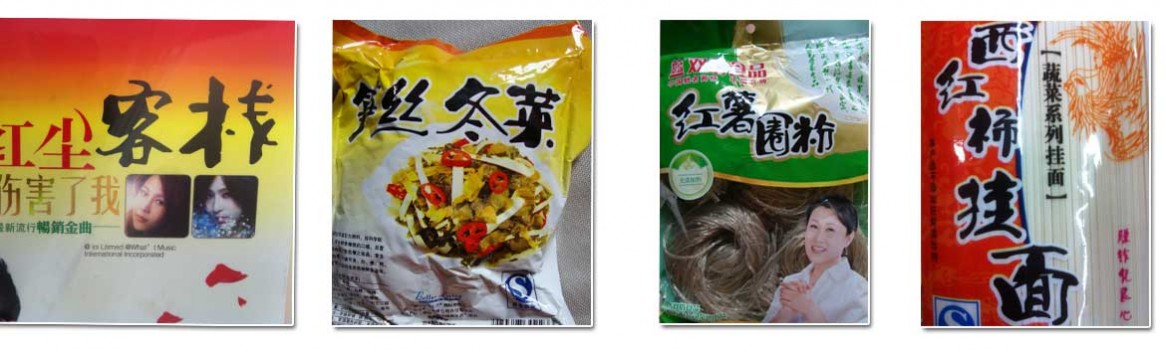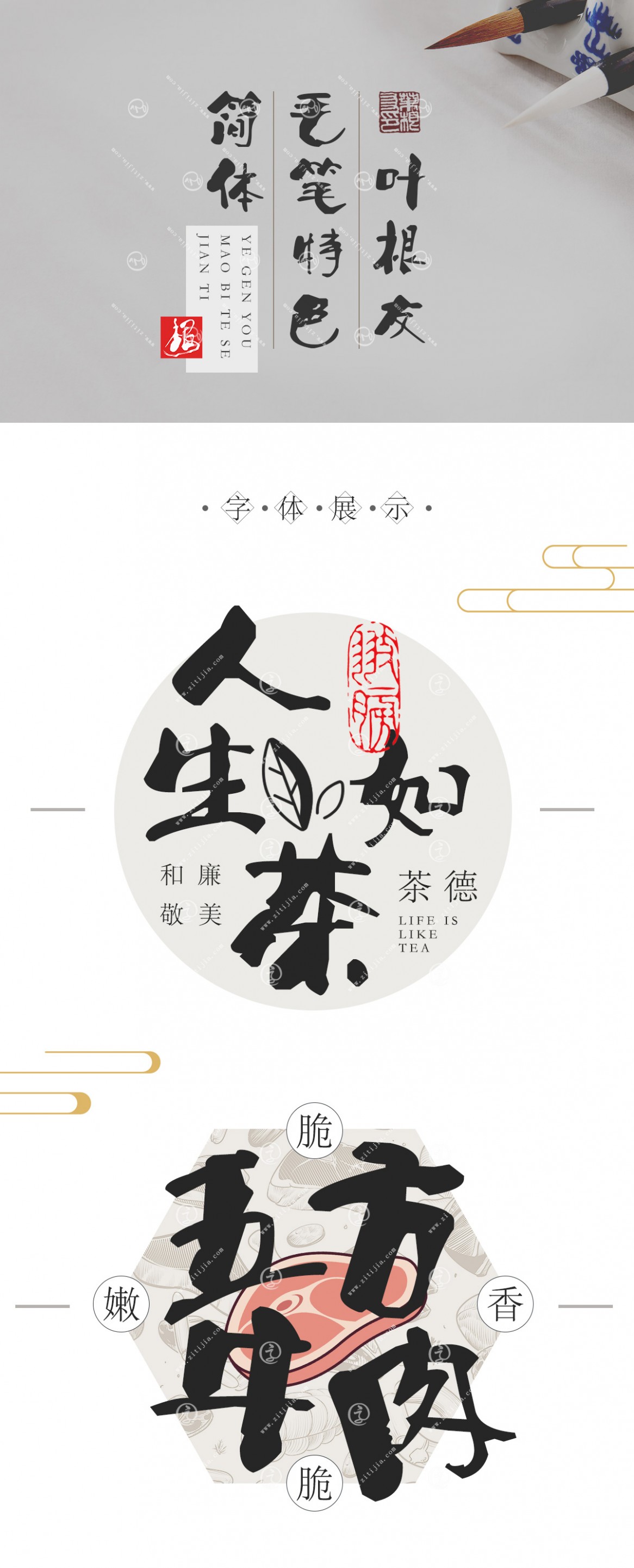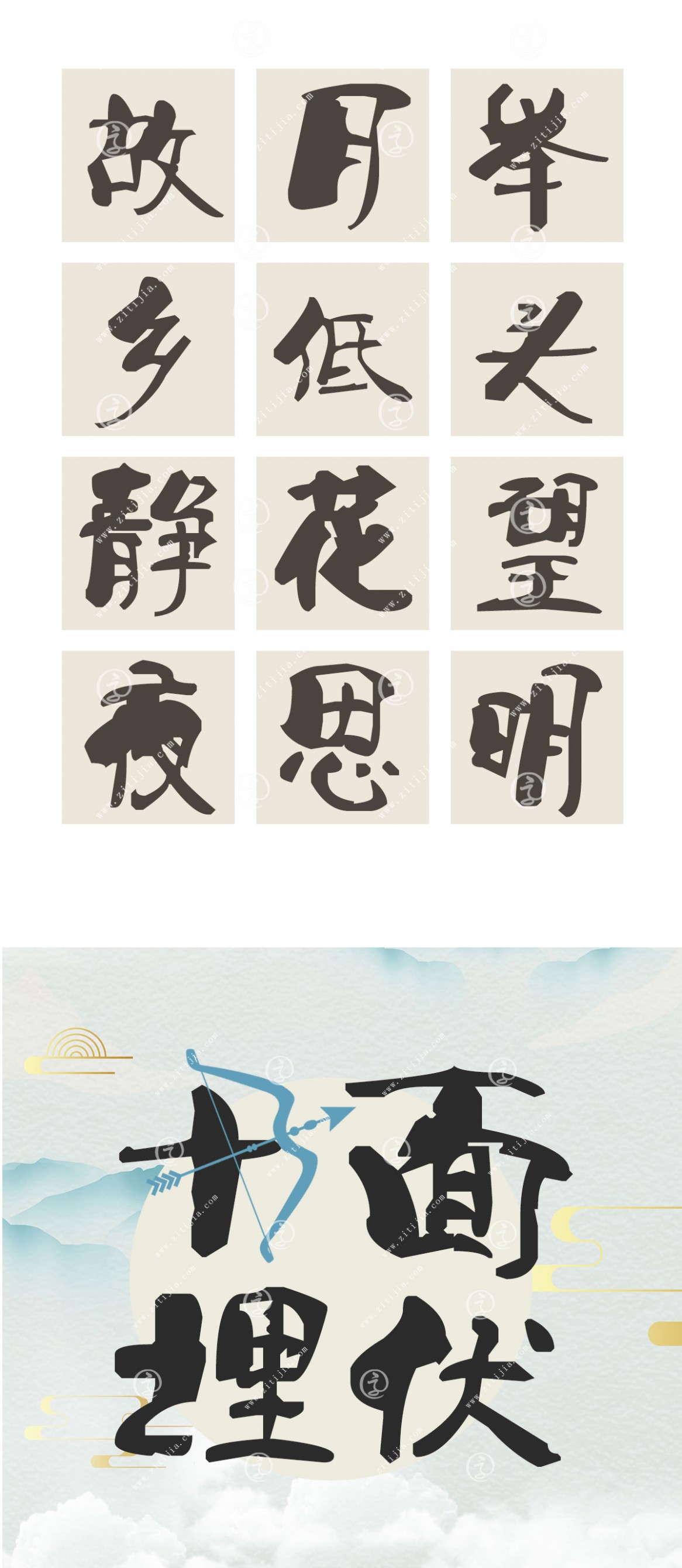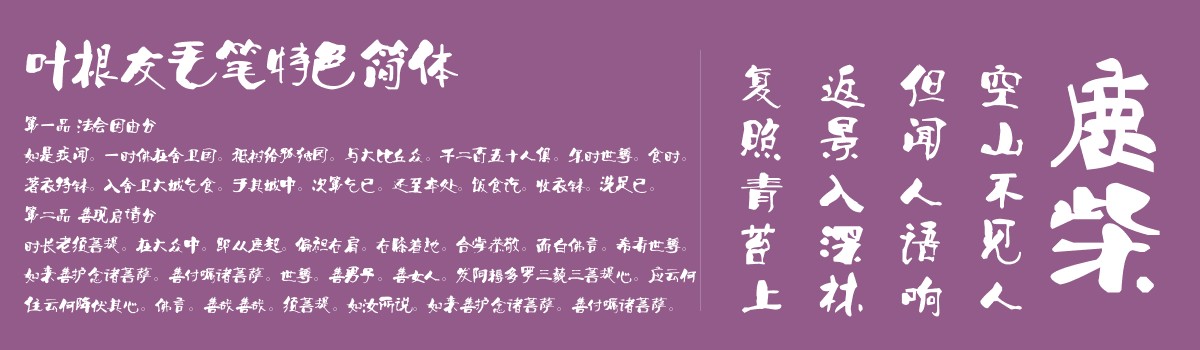
叶根友毛笔特色简体
字体作者:叶根友
创作年代:2007年
字体介绍
叶根友毛笔特色简体被列为叶根友字体系列最受欢迎的字体之一。
一款具有独特气质的毛笔书法字体,浑厚自然的笔画,使书法与现代审美相结合,叶根友毛笔特色简体字体是一款有隶书风格的手写字体。
简洁明了,笔画有粗有细,有正有奇,字型独特创意的一款字体,该字体特色明显,打破传统毛笔书法写法,自创一派,用笔大胆而干练,在粗与细的对比中,体现了中国汉字千变万化的特征,只要有想象,只要有创意,书法字体也可以完全被创意包围
创作记事
2007年7月,初创该字体字稿
2007年7月,发行叶根友毛笔特色简体1.0版本
字体应用